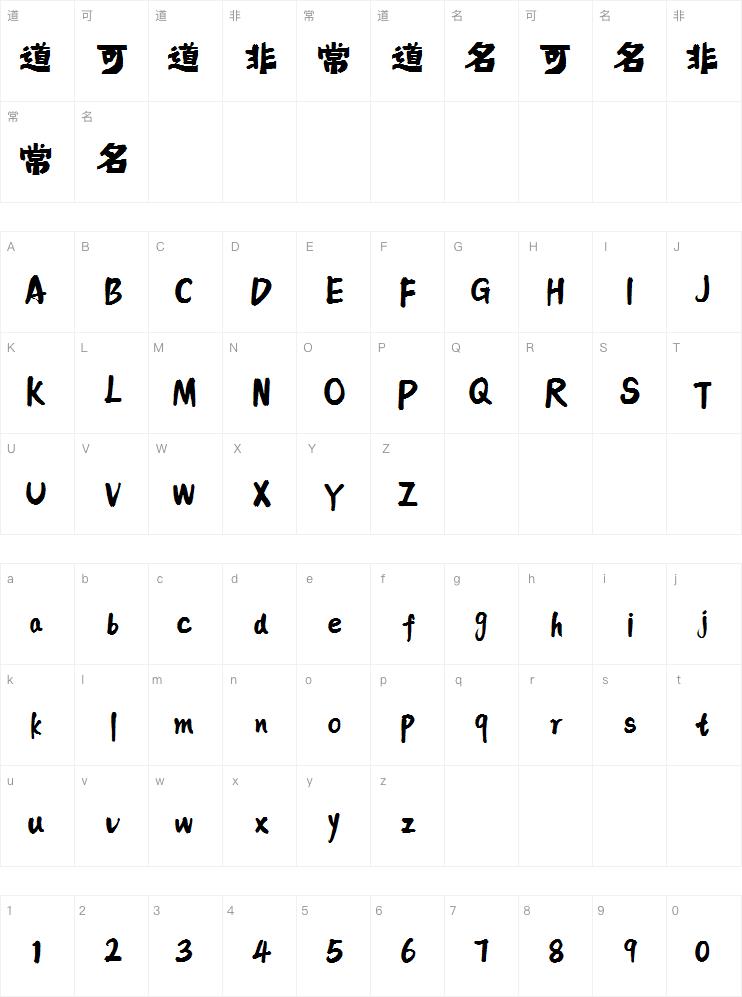
潮字社暗送秋波掌简繁 挥洒是一款随性朴拙、笔触饱满的毛笔字体。结构重心偏移,打破对称平衡;运笔粗重扎实,边缘带有自然的毛糙感,棱角分明又不失朴拙。整体将黑体的简洁与书法的笔触变化结合,创造出兼具现代感与神秘感的新字体。适用于文创产品、书籍装帧、标题、海报设计等多种应用场景,可以营造出充满张力、神秘诡谲又兼具现代潮流感的效果。